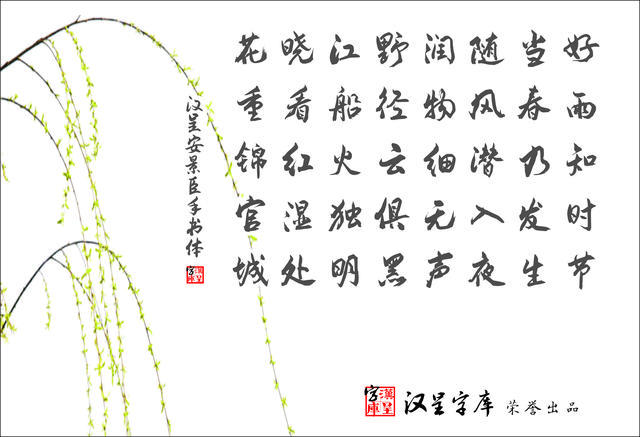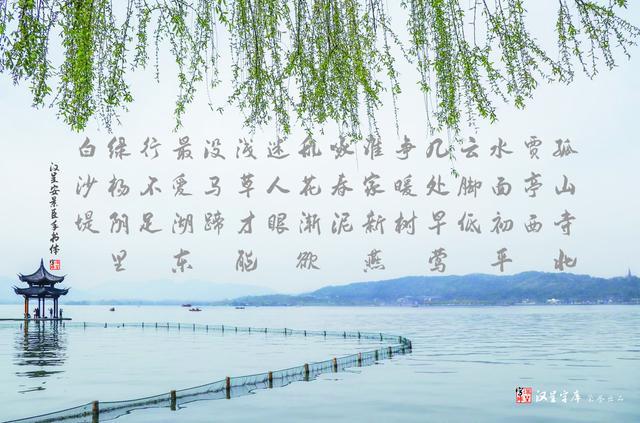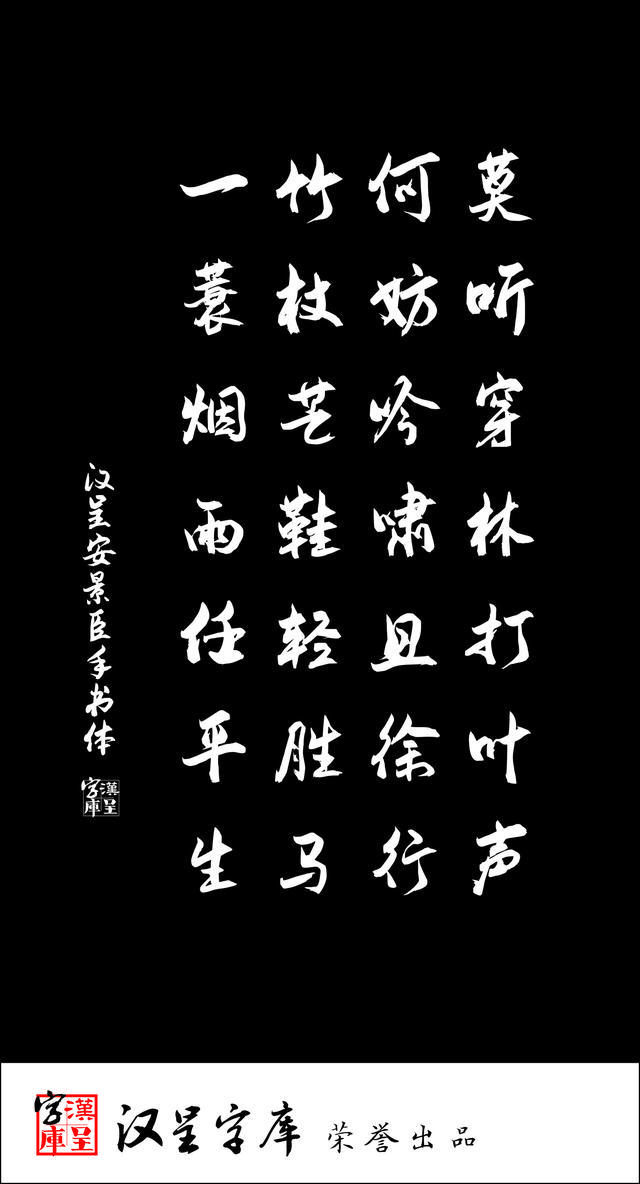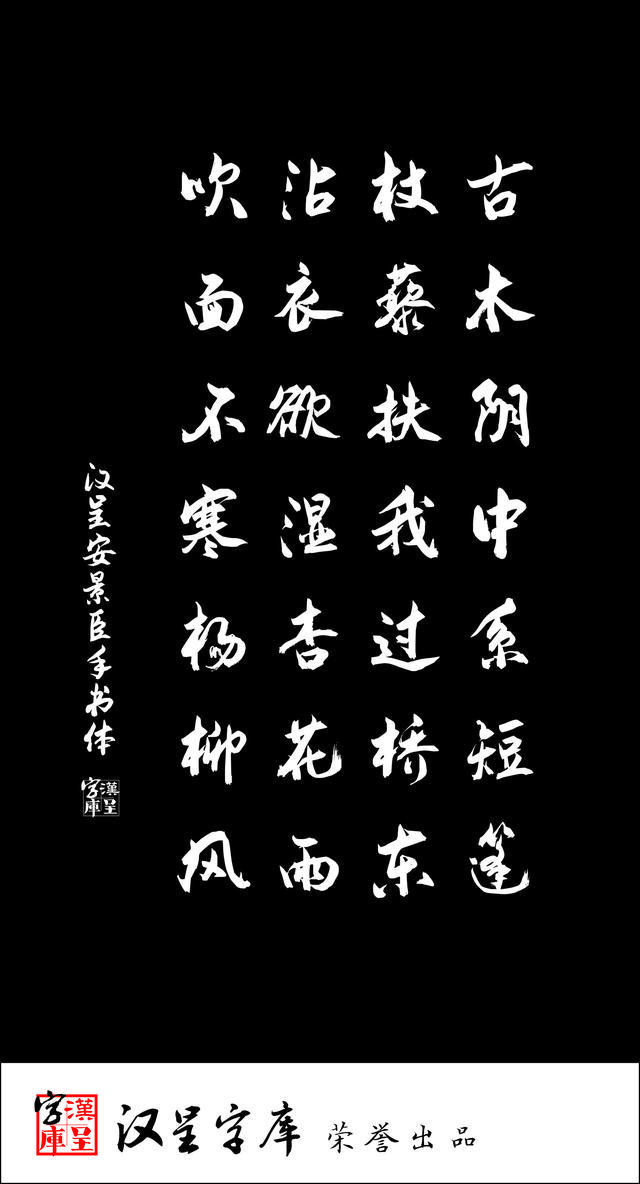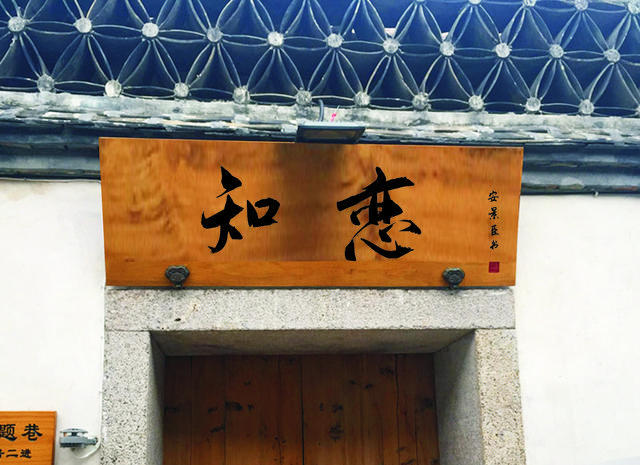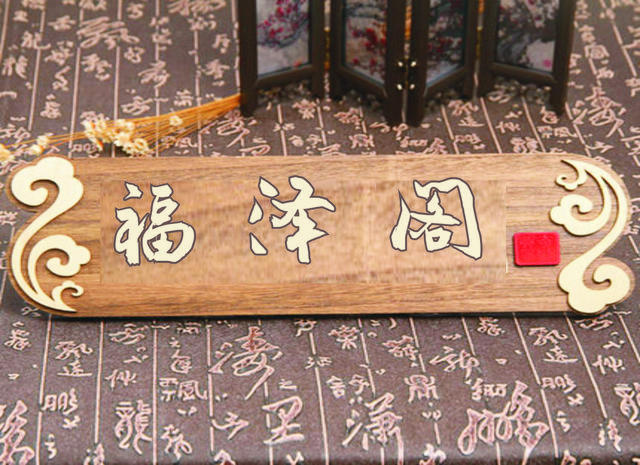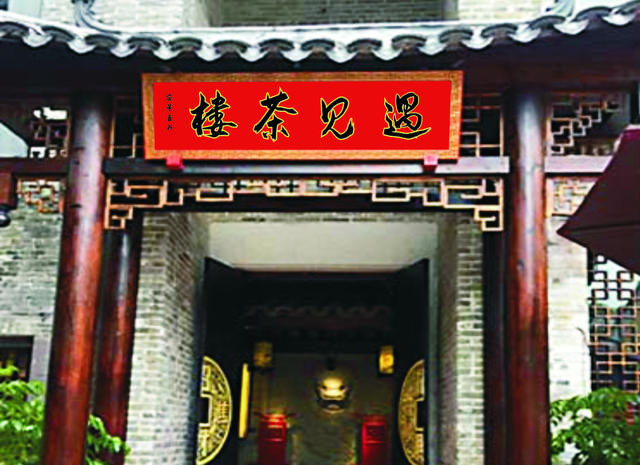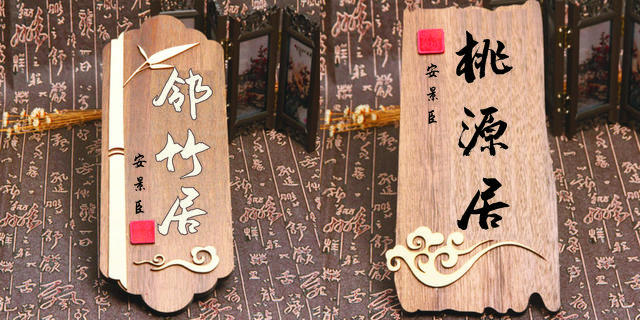
什么是手书?指的是手写的字吗?大多数人不是都用手写字吗?当然指的是手写的字,但在字库行业里,手书通常是指设计的字体打出来的风格接近手写体,最大程度还原手写风格的一类字体。在此之前,曾有数款手书字体风靡网络,取得了很大的成功。但是由于书写者对中国书法艺术研究得不够深入,导致许多高端客户和一些大企业对此类字体不屑一顾,虽然此类字体的普及面非常广,但是,越是普及得广,带来的负面效应越多,人们会认为那就是书法,扭曲了人们的审美,对书法艺术的普及非常不利。因此,编写一款书法味较浓的手书字体迫在眉睫。
汉呈安景臣手书字体欣赏
既然要最大程度还原字体细节,字体写得要足够大,这样书写完扫描,才能尽可能地保留细节,还原真实书写感受。为此,安景臣尝试了采用多个规格大小的字书写,最后确定一张纸写四个字。这样,既能还原真实笔触,还能比一张纸只写一两个字节省纸张。即便是这样,他写这款字体,用去了四包一箱的纸足足两箱!如果在没有写错,一次搞定的情况下,一箱纸足够了。但是,光测试字体书写风格就用去了一些,还有,有时写着写着,发现了更好的书写风格和书写方式,只能从头再来。有时甚至快写到一半了,感觉书写风格要变,变一变更好,于是,没有办法,只能从头写起。就这样,经过反复试验,终于摸索出了合适的风格,决定从头至尾写下去。
汉呈安景臣手书字体欣赏
还有一个问题,便是写错字、丢字的情况。由于六七千字有许多字现在根本用不到,但是也要书写,虽然对于现代汉语来说,几乎没有他不认识的字,但是对于字库当中的字,许多字根本用不到,但是书写字库又必须要写,有些字确实不认识,难免要写错。写错了就要重写,写得不好看的也要重写,无形中加大了工作量。最让人郁闷的是由于书写页上没有提示字,经常丢字、落字,而少写一个字,后面字的顺序就乱了,后面的字不得不重新书写,经过几次重复书写后,不得不写几行,检查一下,生怕丢掉一个字,否则又要重写了。
汉呈安景臣手书字体欣赏
经过从书写风格的确定,到每个汉字的书写,有时一个字要书写好多遍,历经三个多月,终于书写完了字稿。书写完字稿,只是万里长征走完了第一步,还有许多工序才能完成字库的制作。由于字体张数太多了,专业的字库设计公司都不愿意做这类手书字体,没有人配合,就自己尝试做。接下来是扫描字稿。如果用普通的扫描仪,一天扫一百张,也要两三个月能扫描完。想想都头疼,有没有更简便的方式呢?他想到了批量扫描,网上搜一下,还真有这样的设备,于是又购买了批量扫描仪。即便是批量扫描,也费了好几天的时间才把字体扫描进电脑。扫描完了,是切割图片,试了许多网上的免费软件,结果都不好用,无奈,只能买正版。切割过程还算比较顺利,看到自己的图稿变成了一个个单字,心里有了一丝成就感。接下来是文件名命名,修改图片大小等,中途遇到死机或运行不了,就要从头再来,这样折腾了几次,终于达到了要求,但带入字体设计软件,生成字库后,打出的字七扭八歪,字距行距很不一致,如果依次调整,是一个非常大的工程,但现在也没法用啊!于是,找到了网上做字库的朋友,曾经合作过的汉呈字库王天喜老师,王老师说:“如果挨个去调整,繁琐程度不亚于重新制作一套新字库,原因是切片扫描时做得不好,导致后面的字位置很不规范,既已经做到这一步了,看在朋友的情分上,免费帮你调吧!”王老师逐个将字做了调整,又是一个浩大的工程!但王老师调得比较快,大约半个多月,字库终于调整好了,成了能用的字库。这款字库是他们共同努力的成果啊!为此将此字体命名为汉呈安景臣手书体,并注册了版权。喜欢安景臣字体的朋友可以到汉呈字库下载。
汉呈安景臣手书体欣赏
从这件事可以看出,术业有专攻。王老师不但字写得好,做字库的技术也是一流。而安景臣的字库技术扔在学习提高中。看花容易绣花难,想要真正掌握一项技术,就要放低姿态,向优秀者学习,自己才能不断进步!
汉呈安景臣手书字体应用
安景臣先生书法欣赏